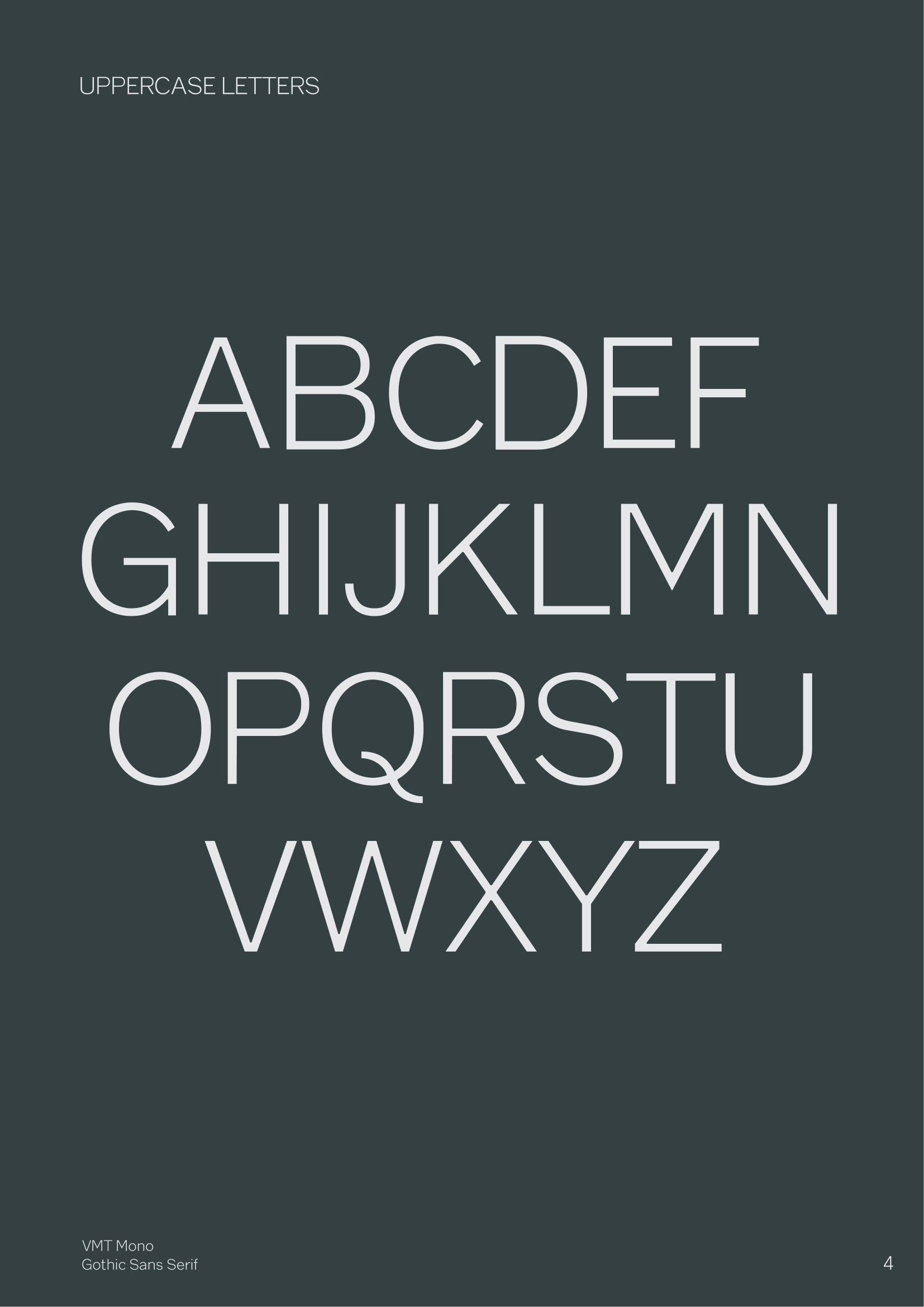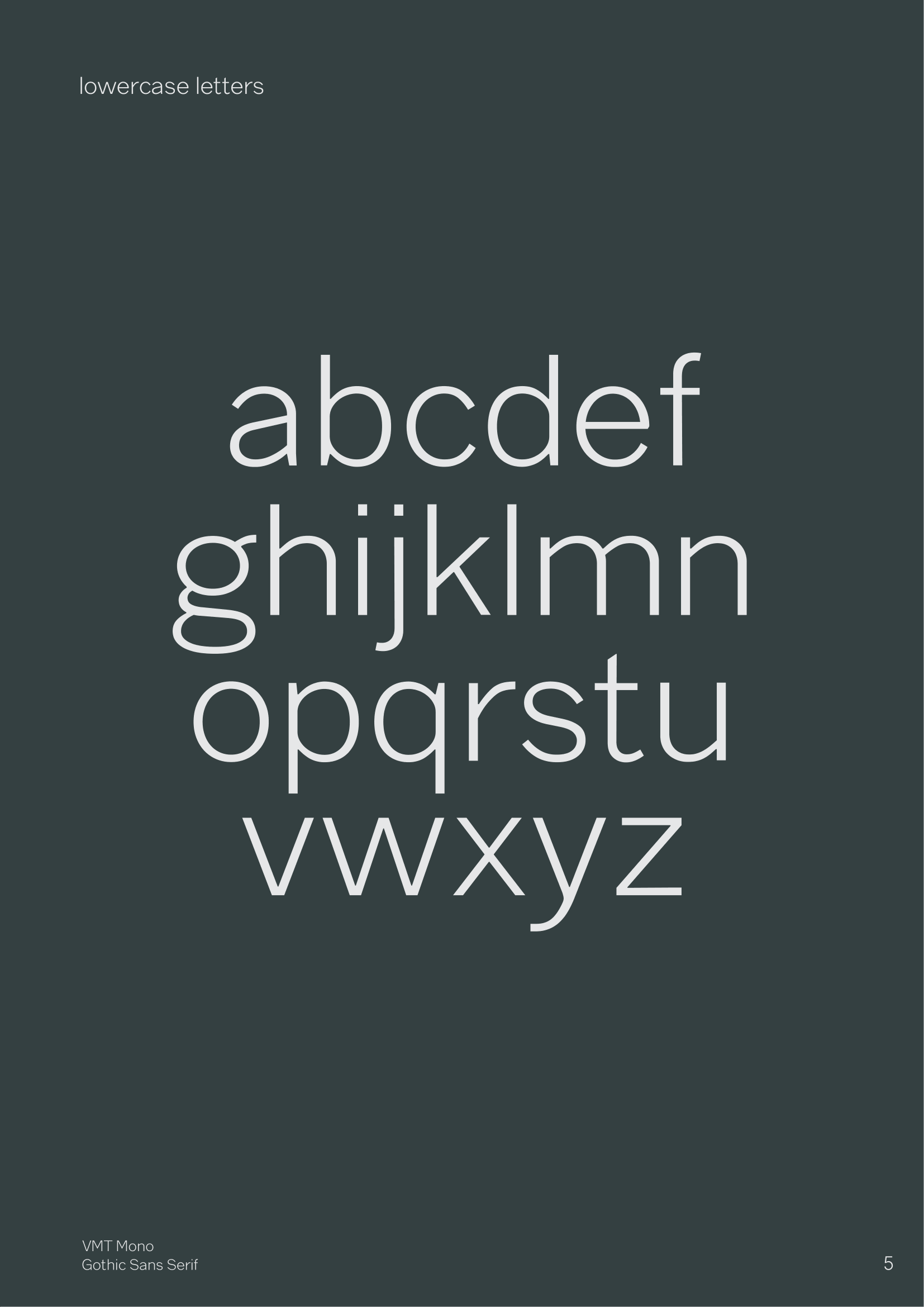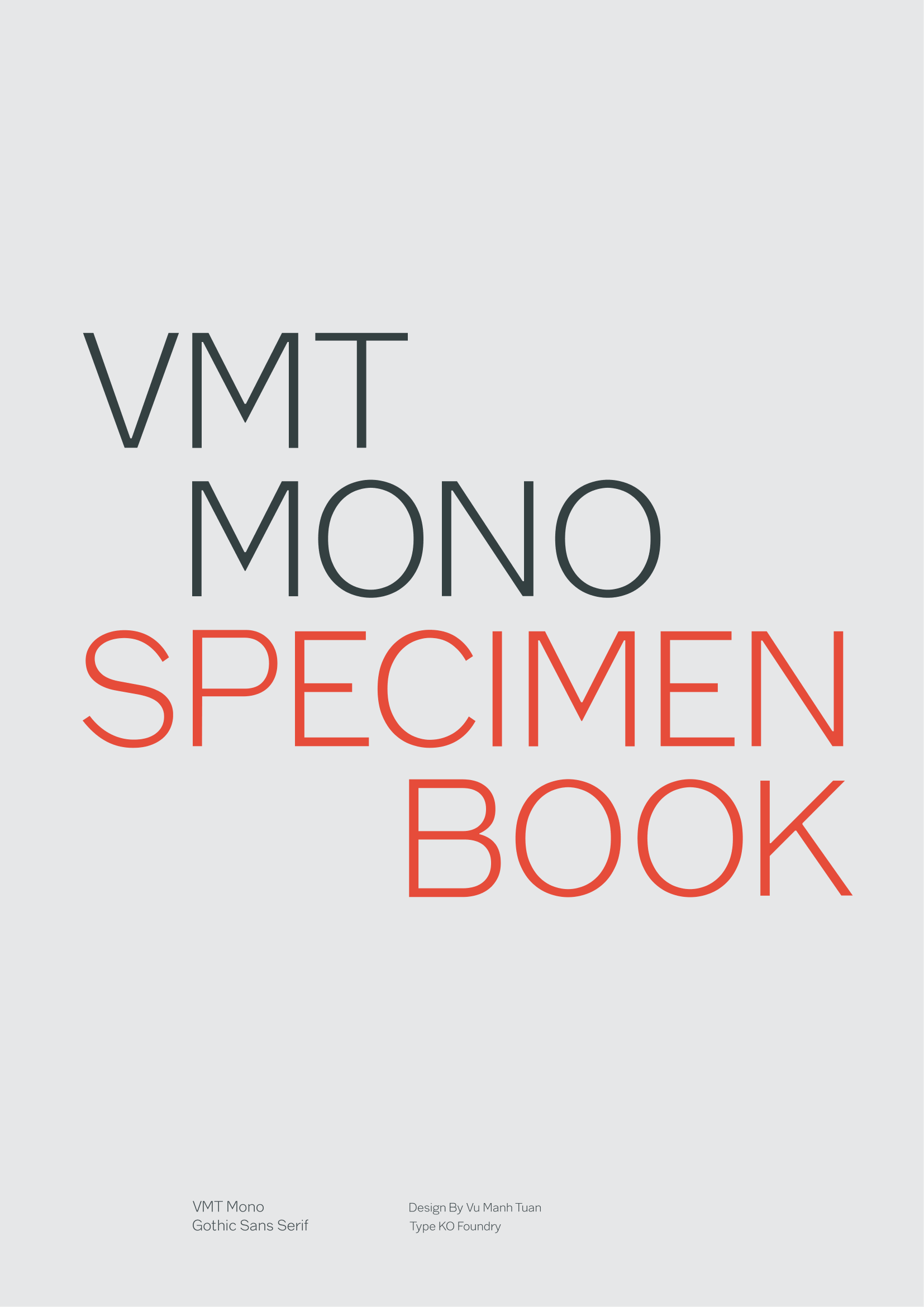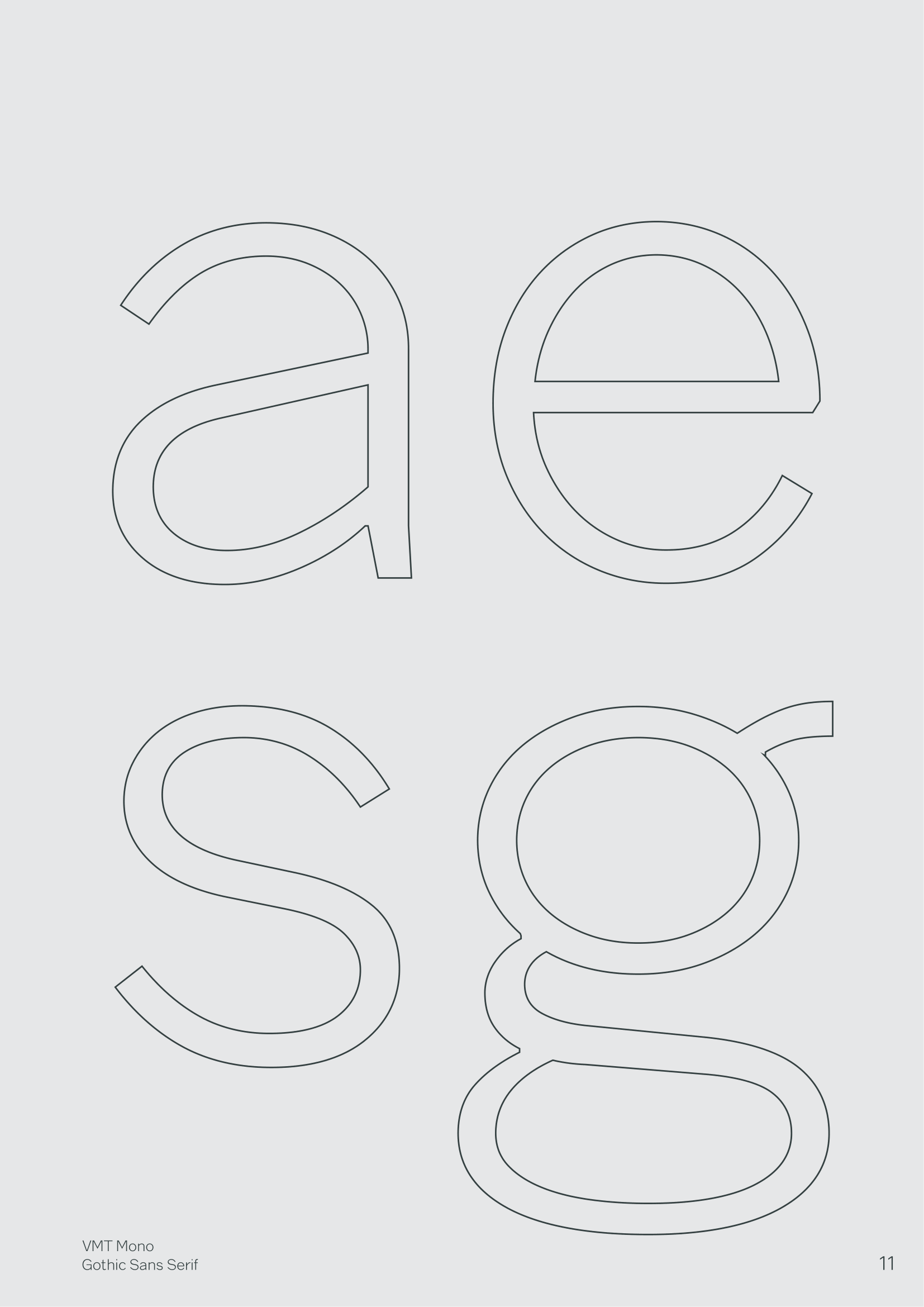
VMT Monotone
Về VMT Monotone: VMT Mono được dựa trên typeface Monotone Gothic, được tạo ra bởi Morris Fuller Benton (American Type Foundry). Các ký tự đã được tinh chỉnh để phù hợp với môi trường kỹ thuật số nhưng vẫn giữ được diện mạo nguyên bản của typeface gốc. VMT Mono iện đại, tự do, thoáng đãng, đồng thời thân thiện — sans serif nhưng không mang cảm giác công nghiệp
Grotesque Sans Serif
Vũ Mạnh Tuấn
VMT Monotone
Quality
VMT Monotone
Delicate
VMT Monotone
Refinement
VMT Monotone
Personality Hire
VMT Monotone
Monotone Gothic is a sansserif typeface designed by Morris Fuller Benton for the American Type Founders ATF It was developed as part of Bentons systematic approach to building large Gothic families where related designs were created in different weights and proportions
VMT Monotone
Monotone Gothic is essentially a lighter more extended companion to Franklin Gothic sharing its industrial earlymodern American grotesque character but with a more even calm stroke contrast and wider spacing that gives it a more open less aggressive appearance Only one weight was produced and it was not widely expanded or copied by other foundries which makes it a relatively rare but important step in Bentons effort to refine functional sansserif typography for advertising and print in the early twentieth century